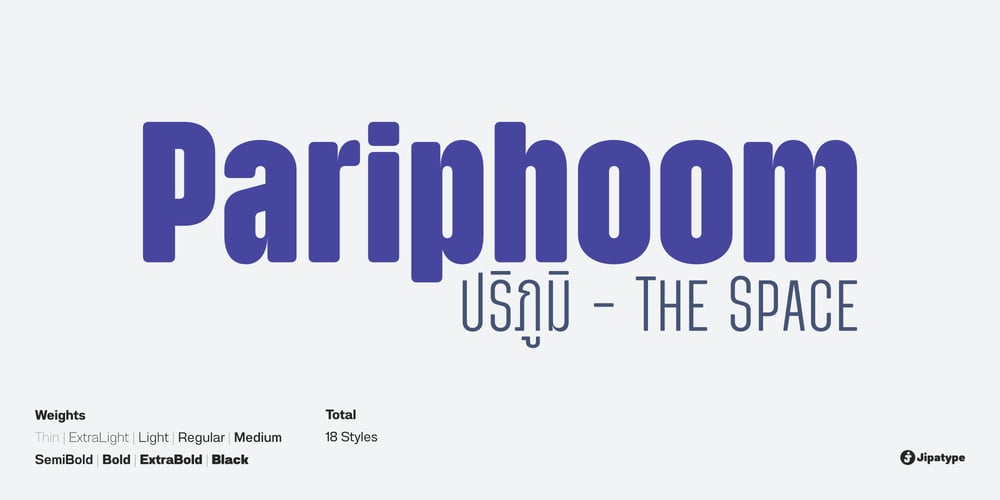
Pariphoom
Pariphoom font
Pariphoom Font Family was designed by Anupap Jaichumnan and published by Jipatype. Pariphoom contains 18 styles and family package options. ขอแนะนำ Pariphoom แบบอักษรอันโฉบเฉี่ยวและทันสมัย เหมาะสำหรับงานออกแบบหลากหลายประเภท ด้วยอักษรแบบ sans-serif condensed และมุมโค้งมน แบบอักษรนี้ให้ความสมดุลที่ระหว่างความเป็นทางการและความเข้าถึงได้ง่าย ชื่อปริภูมิมาจากภาษาไทย แปลว่า “Space” และเช่นเดียวกับชื่อของมัน ฟอนต์นี้สามารถให้พื้นที่มากขึ้นในงานออกแบบของคุณ ไม่ว่าคุณกำลังสร้างสื่อสำหรับสร้างแบรนด์ พัฒนาแคมเปญการตลาด หรือออกแบบเว็บไซต์ Pariphoom มอบความยืดหยุ่นและความอเนกประสงค์เพื่อให้ได้รูปลักษณ์ที่คุณต้องการ Pariphoom มาพร้อมกับรูปแบบที่แตกต่างกันถึง 18 รูปแบบ สิ่งนี้ทำให้คุณมีตัวเลือกมากมายและมีความยืดหยุ่นในการใช้งานในหลากหลายบริบท นอกจากนี้ ฟอนต์นี้รองรับหลายภาษาสำหรับภาษาต่างๆ มากมาย แต่นั่นไม่ใช่ทั้งหมด Pariphoom มาพร้อมกับฟีเจอร์ Opentype เจ๋ง ๆ เช่น Small Caps และ Tabular ซึ่ง Small Caps เป็นวิธีที่ยอดเยี่ยมในการเพิ่มความหลากหลายให้กับงานออกแบบของคุณโดยใช้ตัวพิมพ์ใหญ่แทนตัวพิมพ์เล็ก ในขณะเดียวกัน Tabular ก็สมบูรณ์แบบสำหรับการสร้างตารางและจัดตำแหน่งตัวเลขเพื่อให้ดูเป็นระเบียบมากขึ้น โดยรวมแล้ว Pariphoom ทำให้เป็นตัวเลือกที่ยอดเยี่ยมสำหรับนักออกแบบที่ต้องการสร้างผลงานการออกแบบที่น่าจดจำและมีประสิทธิภาพIntroducing Pariphoom, a sleek and modern typeface that is perfect for a wide range of design projects. With its condensed sans-serif design and rounded corners, this font offers a unique balance of professionalism and approachability. Derived from the Thai language, the name Pariphoom means “Space” and just like its name suggests, this font can give you more space in your design. Whether you’re creating branding materials, developing marketing campaigns, or designing websites, Pariphoom offers the flexibility and versatility you need to achieve your desired look. Pariphoom comes with 18 different styles. This gives you plenty of options to choose from and the flexibility to use it in various design contexts. Additionally, this font offers multi-language support for a wide range of languages. But that’s not all – Pariphoom comes with some cool Opentype features such as Small Caps and Tabular. Small Caps are a great way to add variety to your design by using small capital letters instead of lowercase letters. Meanwhile, Tabular is perfect for creating tables and aligning numbers for a more organized look. Overall, Pariphoom making it a great choice for designers who want to create memorable and effective design projects.